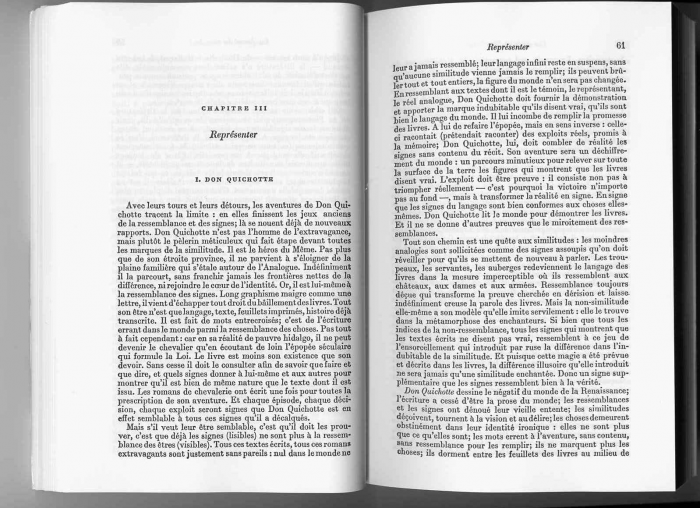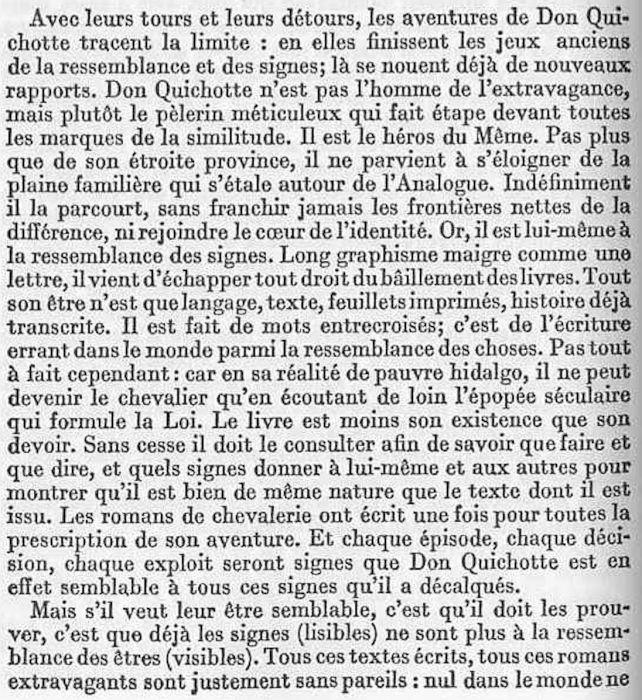
Suche Font der Pariser Gallimard Publikationen 1960er/1970er
bin auf der Suche nach der Schriftart in den Pariser Gallimard Publikationen aus den 1960er und 1970er Jahren.
Betrifft z.B. die folgenden Publikationen:
Certeau, Michel de: L'écriture de l'histoire, Paris: Gallimard 1975.
Foucault, Michel: L'archéologie du savoir, Paris: Gallimard 1969.
Gille, Bertrand: Histoire des techniques. Technique et civilisations, technique et sciences, Paris: Gallimard 1978.
Beispielgrafiken sind aus:
Foucault, Michel: L'archéologie du savoir, Paris: Gallimard 1969, S. 60.
Hast Du davon noch eine besserere Version mit mehr Details? So könnte das vieles sein ... hat eine gewisse Bodoni Anmutung, aber für eine genauere Bestimmung fehlen bei der Qualität die Details.
Die Auflösung macht es in der Tat etwas schwierig, aber ich würde auf Didot tippen. Das Q spricht zwar eher für eine Bodoni, aber Gallimard hat m. W. wenigstens seit der nrf(1909 folgende) immer Didot für die Titel eingesetzt. Es spricht dan einiges dafür, dass sie dann auch für den Fließtext dabei geblieben sind, eine klassizistische Schrift ist es ja allemal. Zudem hat Gallimard m.W. lange bei der Druckerei Didot drucken lassen.